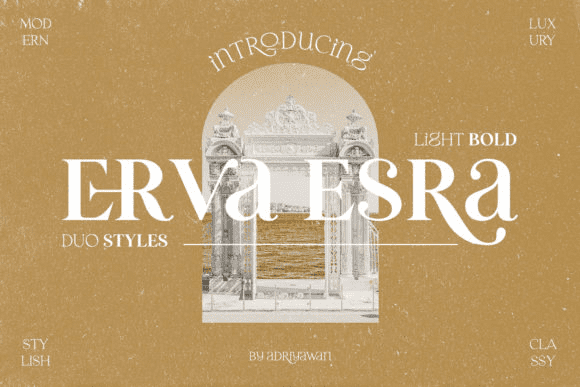
Название: Erva Esra Font (2021)
Erva Esra - это модный, крутой и стильный шрифт с засечками.
Независимо от темы, этот шрифт станет прекрасным дополнением к вашей библиотеке шрифтов, поскольку он способен улучшить любое творение.